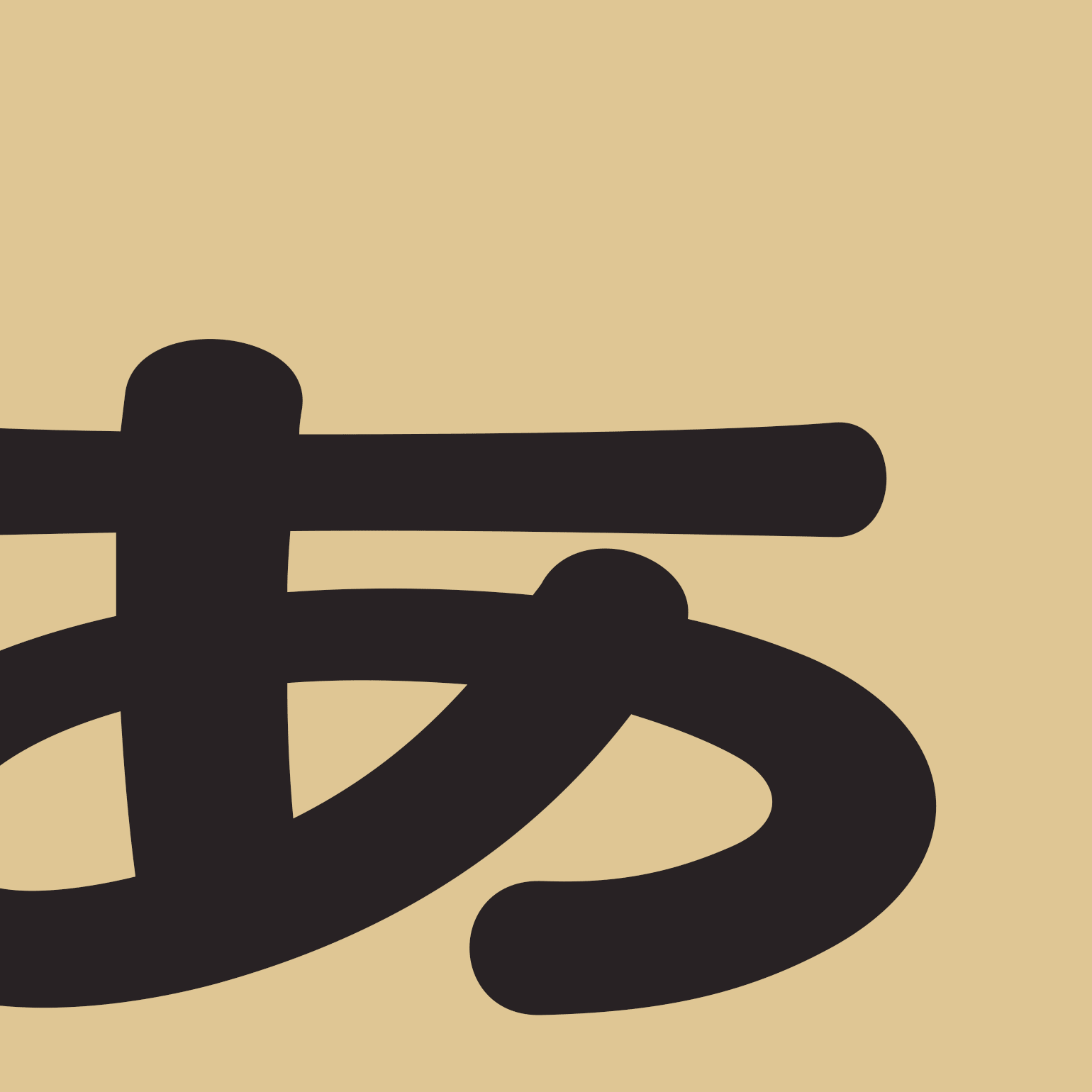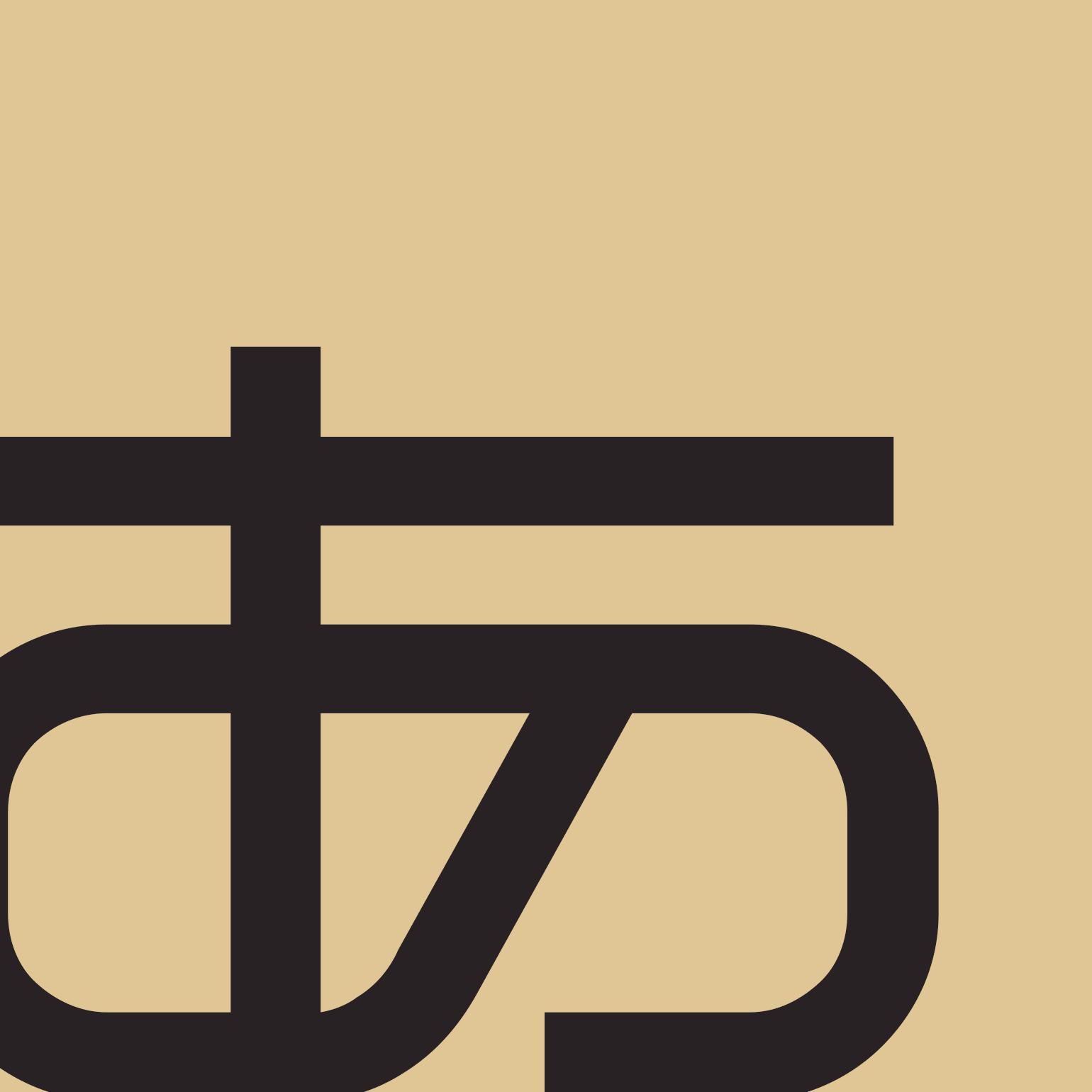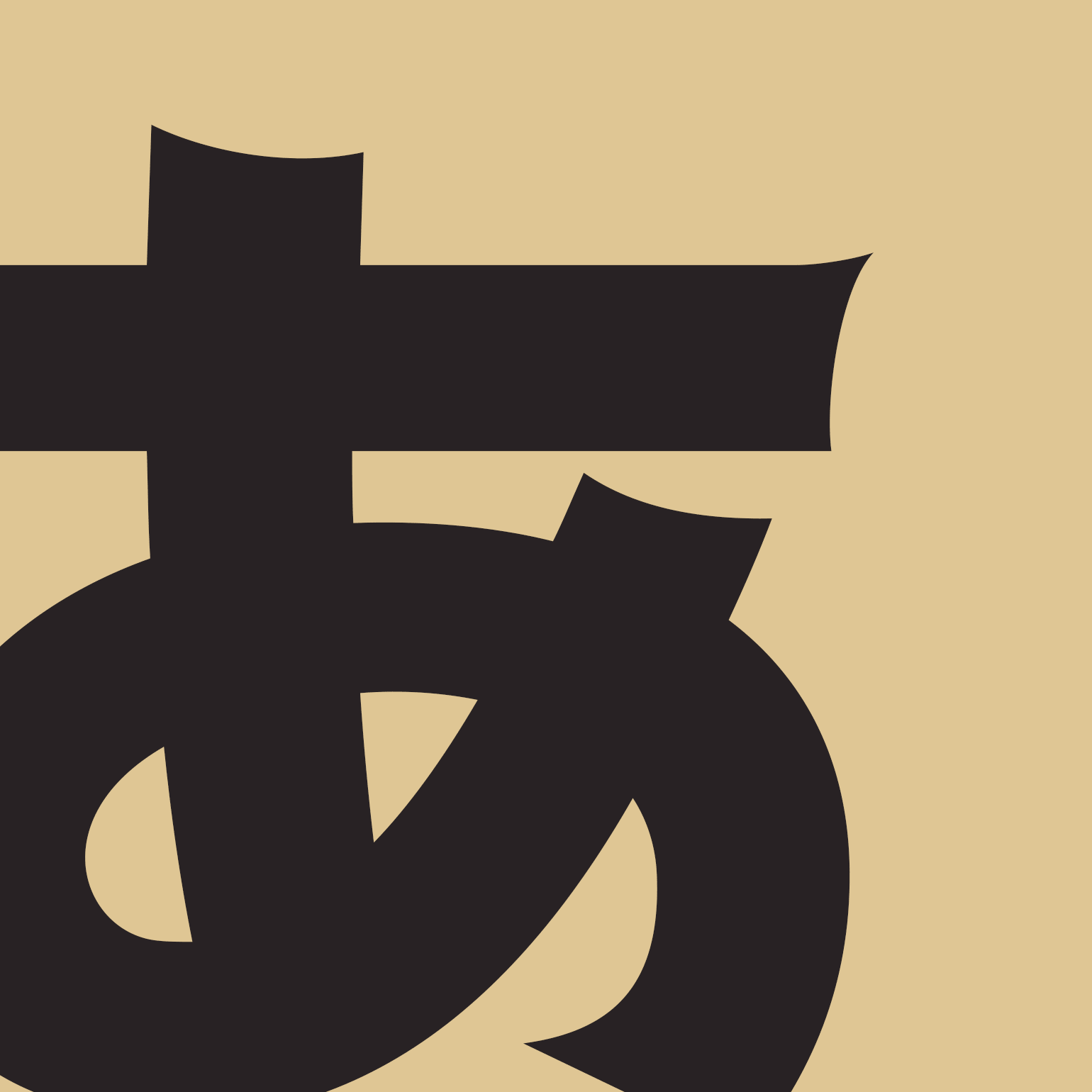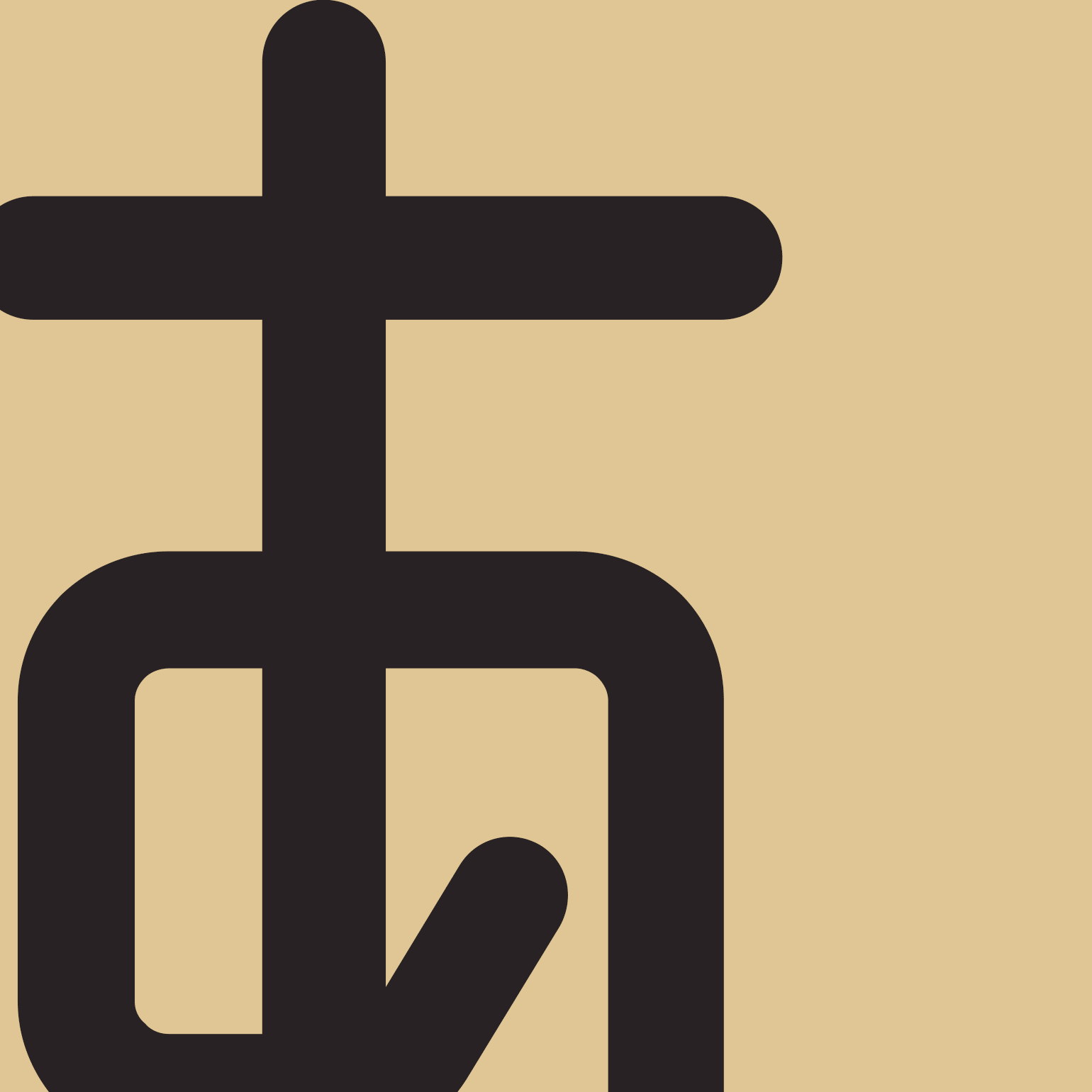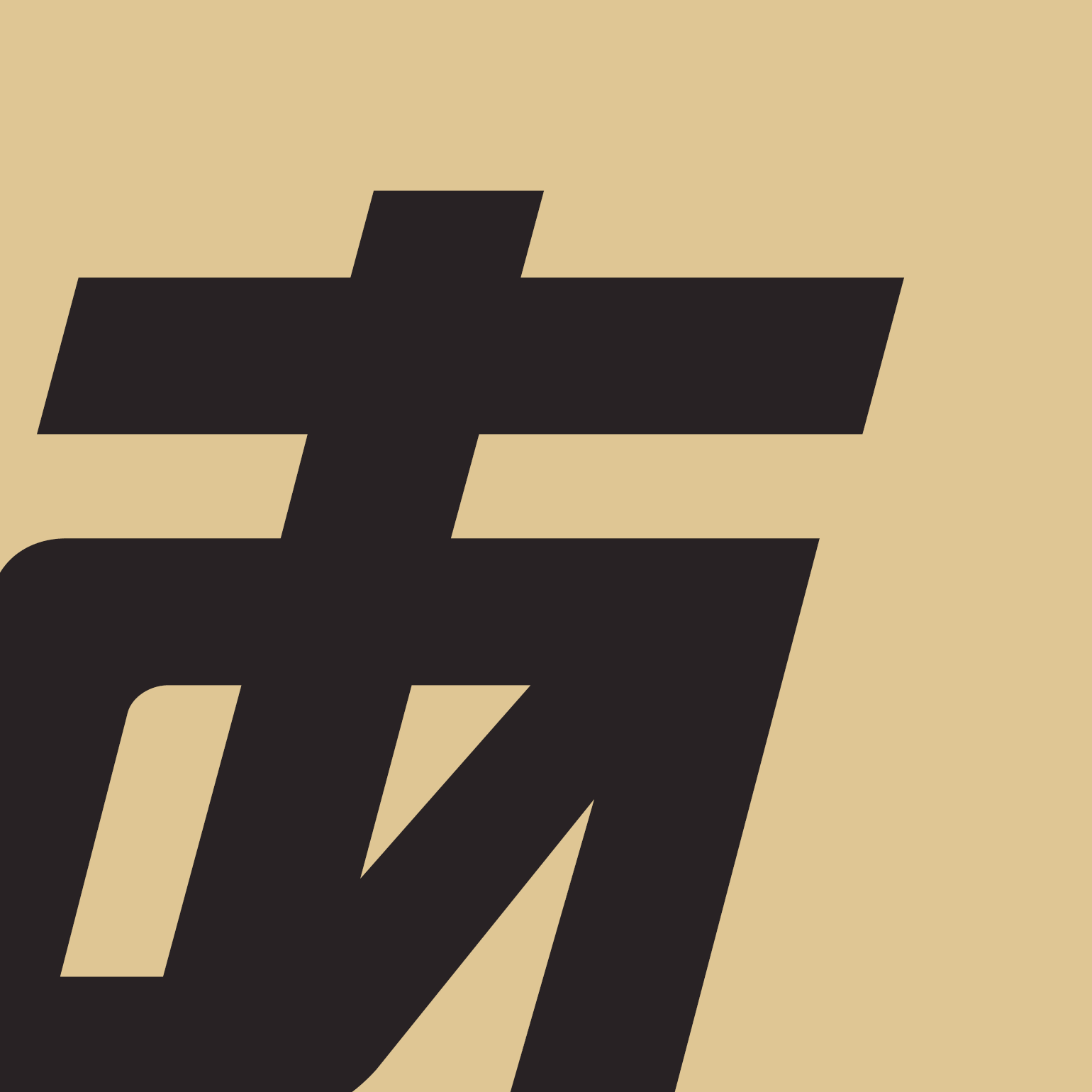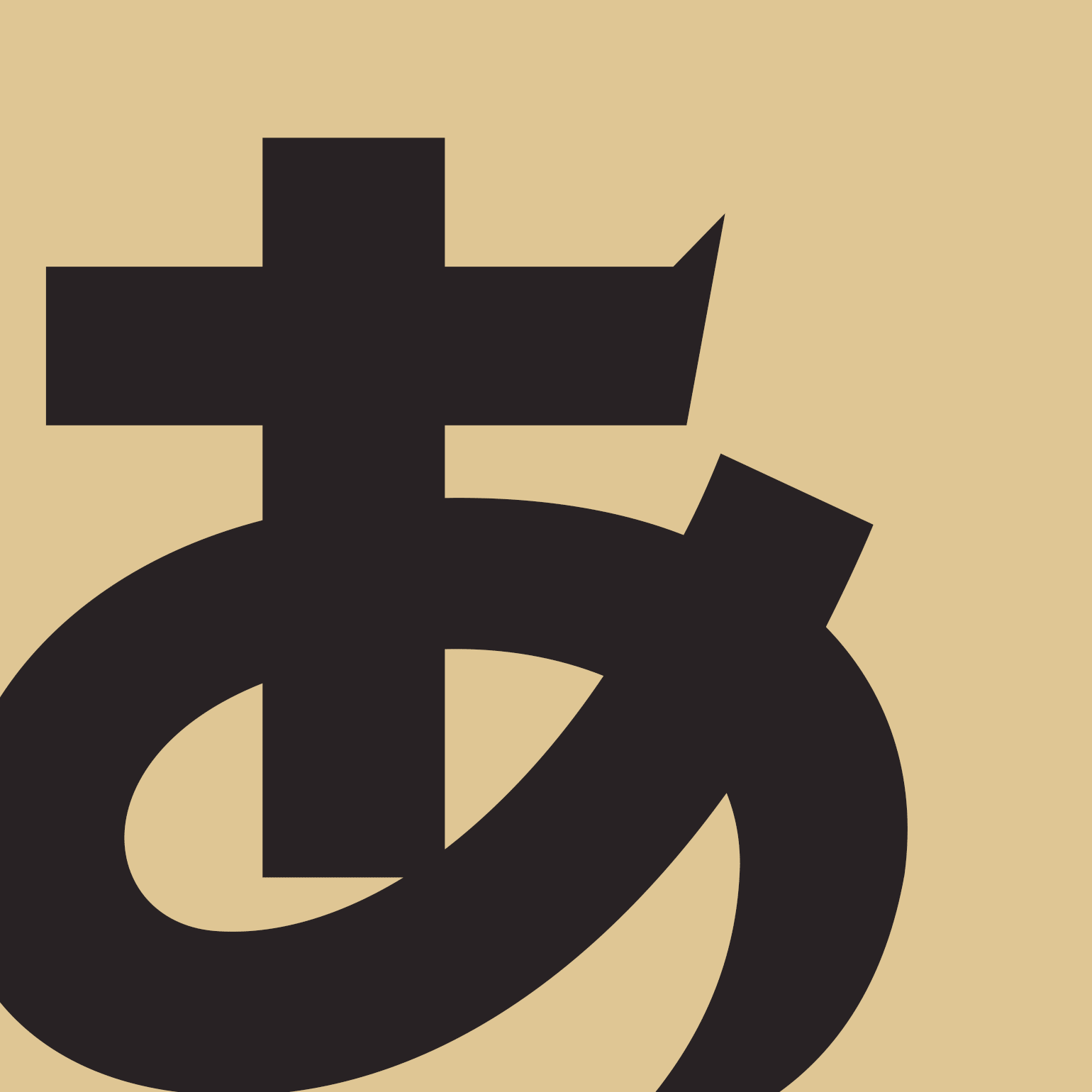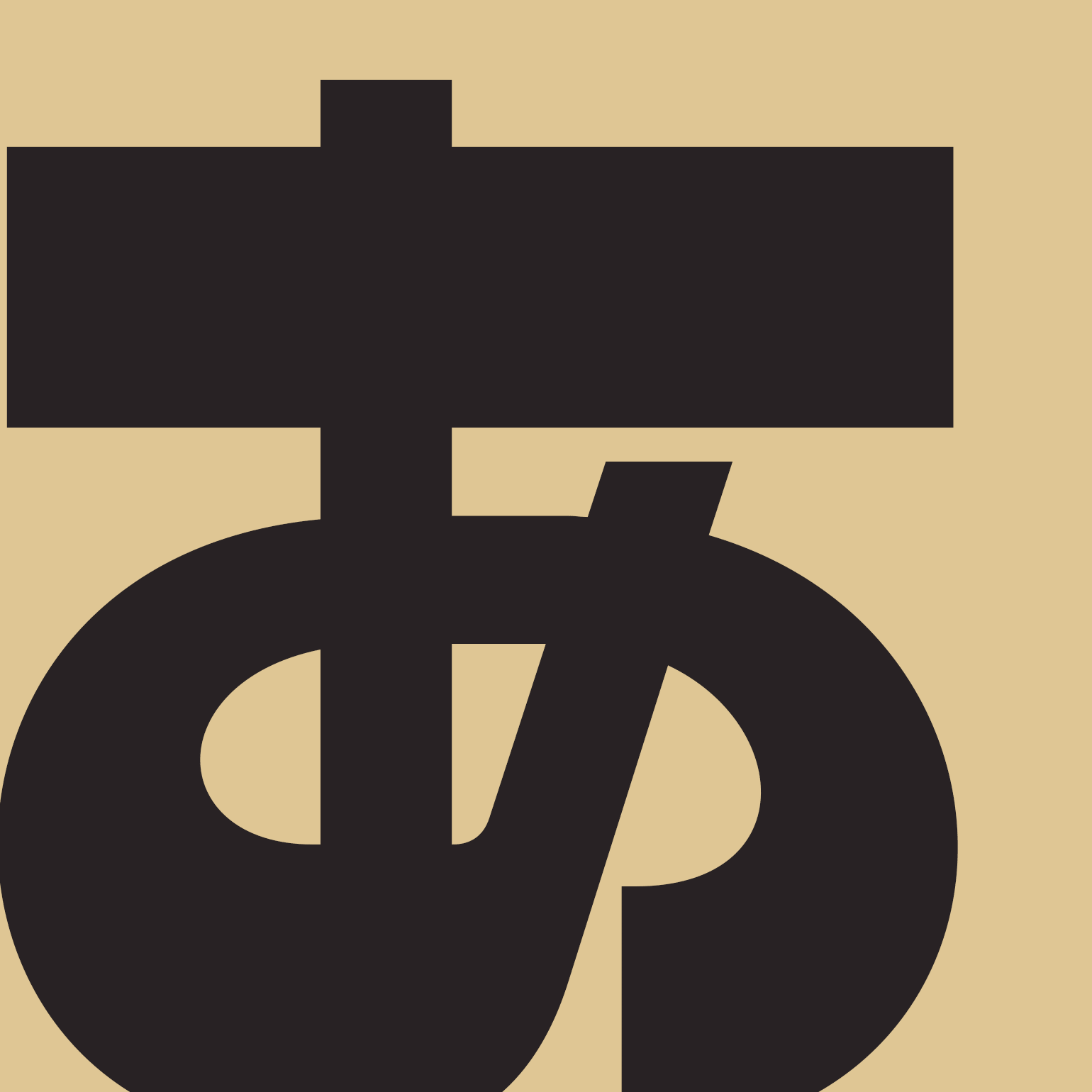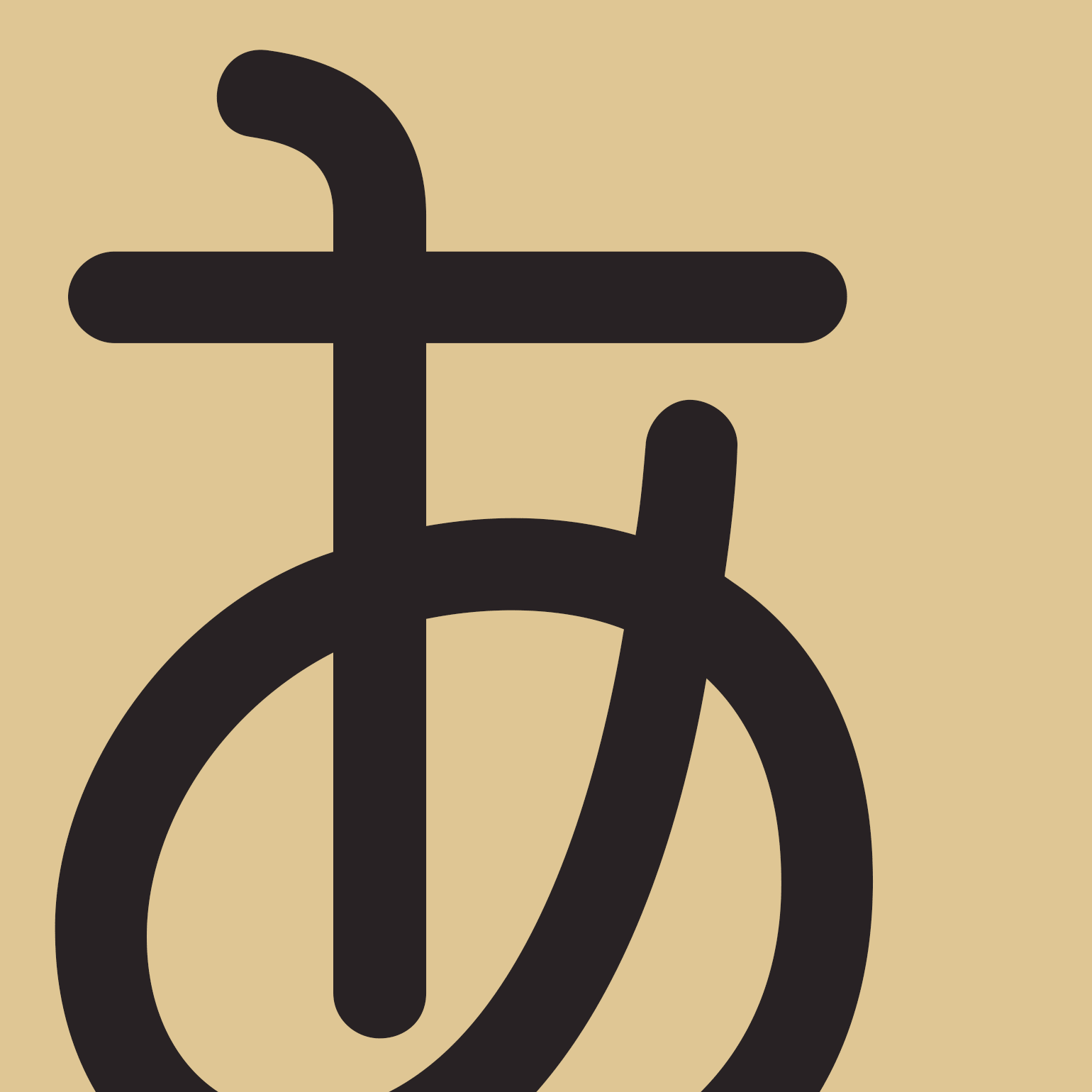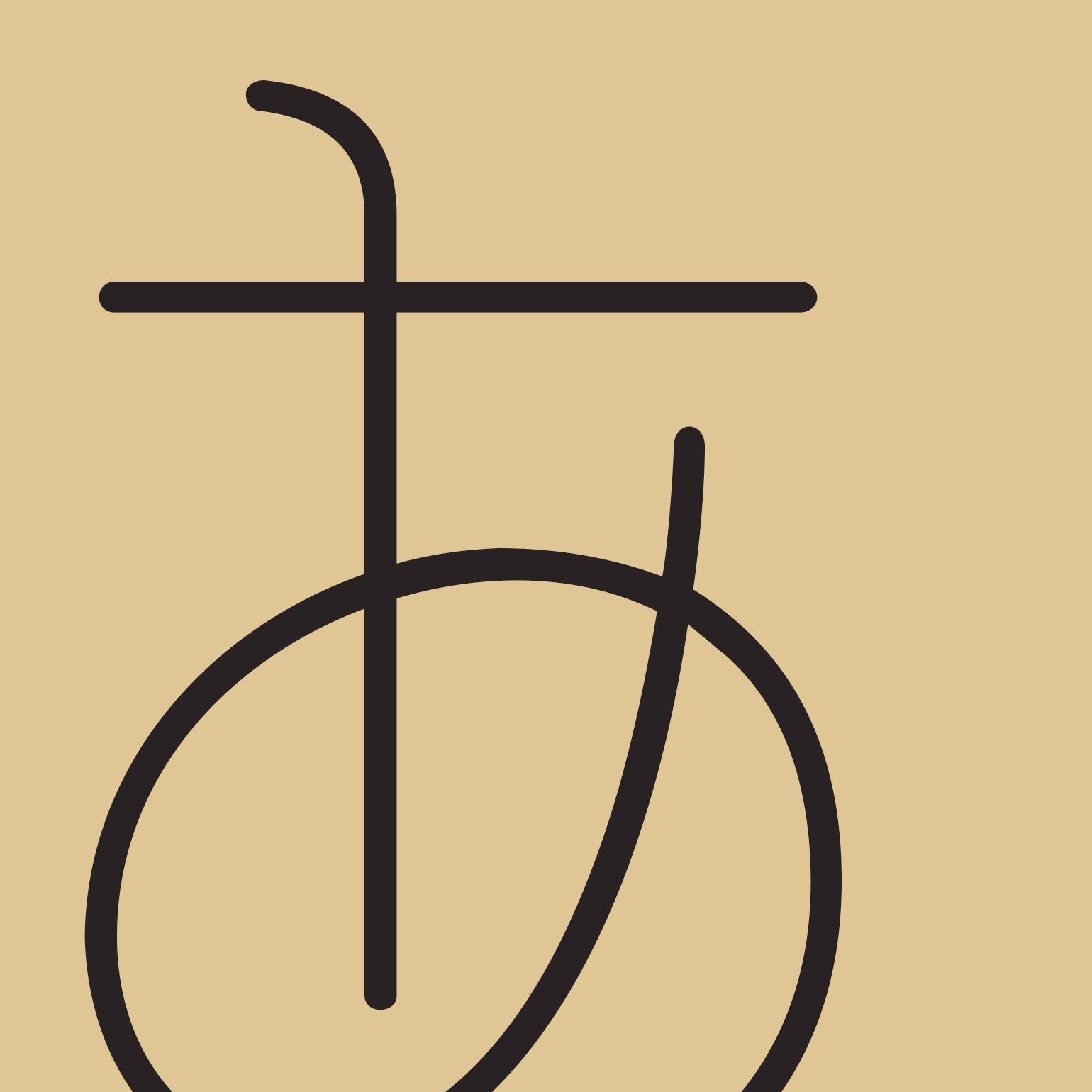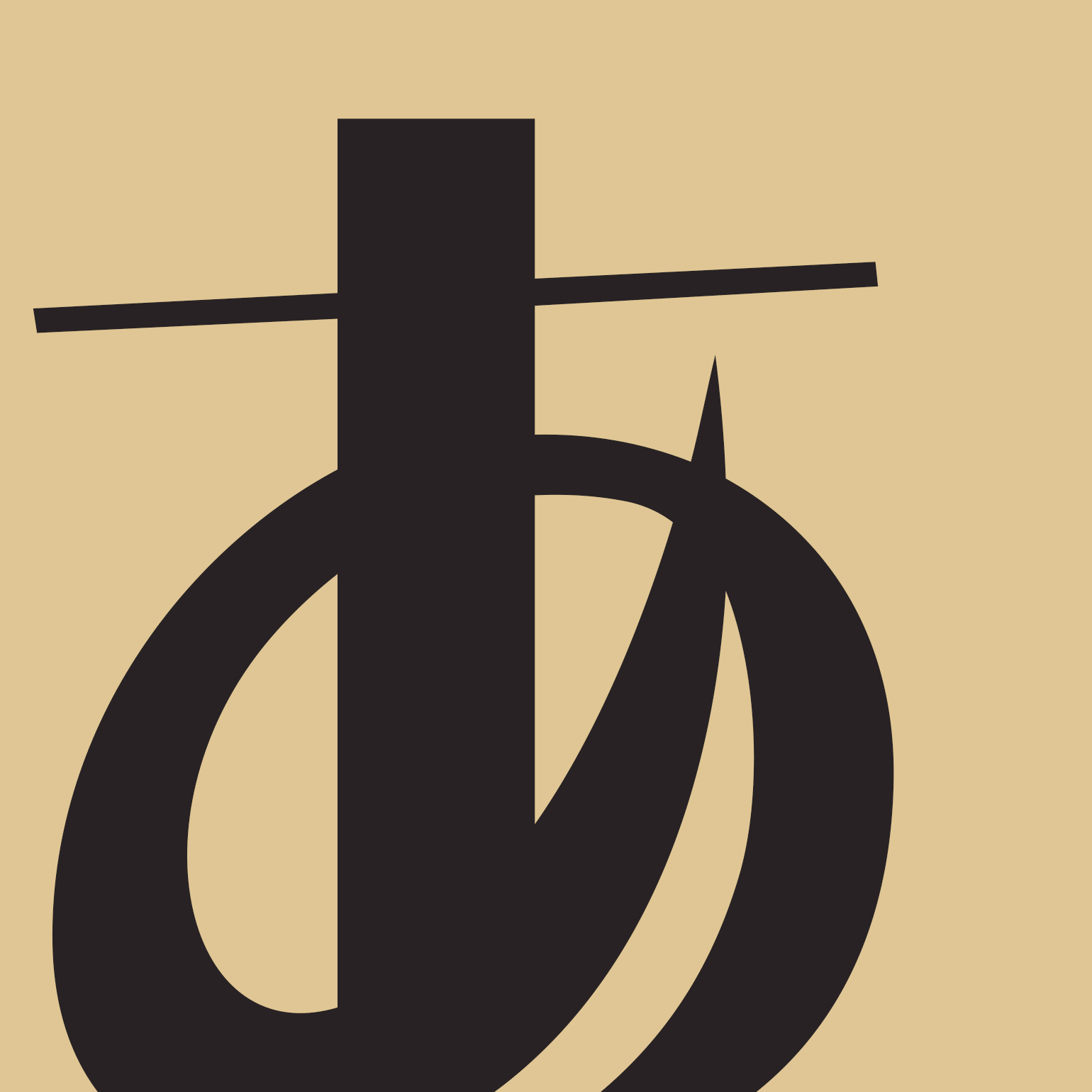
シンプルな手書き風の書体でありながら、デザイン性を損なうことなく、かわいらしさがあふれています。新鮮で自然な雰囲気が感じられ、人々に心地よさを与えます。まるで旅先で気ままに綴られた日記のような自由さとリラックス感が漂っています。
素朴な線幅と、わずかにざらついた質感を持つ手書き風の書体です。全体的に素朴で親しみやすい雰囲気があり、やや左に傾いた字形が視覚的な美しさとバランスの良い文字組みを実現します。製品パッケージやアニメーション、ゲーム、ビデオ制作など、さまざまな用途で活用できます。
この書体は、丸みを帯びた柔らかな線と変化に富んだデザインが特徴です。字形は大胆で、遊び心にあふれています。ハイライトのアクセントが文字に軽やかさを加え、全体的により生き生きとした印象を与えます。絵本や児童書、広告、アート作品、看板、チラシなど、幅広い用途で多彩な表現が可能です。
この書体は、かわいらしい手帳風のフォントです。自由で柔軟な構造に加え、丸い点の筆画が視覚的な楽しさを演出し、個性を際立たせています。全体的に無邪気で純粋な雰囲気があり、温かく癒やしのある印象を与えます。
このフォントは素朴で自然な雰囲気と自由な筆致が特徴です。細やかな筆触で描かれた丸みのある線が、温かみと手描きの味わいを感じさせます。高い視覚的表現力を持ち、手帳、児童書、動画 Vlog、個性派ブランドデザイン、広告など幅広い用途に適しています。
清新で自然な雰囲気を持つフォントです。流れるような筆致にブラシの質感を加え、自由で伸びやかな印象を与えます。意図的に引き延ばした点画が、力強さとリズム感を演出します。広告、タイトル、説明文、映画字幕など、多様なデザイン用途に適しています。
筆致の太さに変化があり、巧みさを素朴さに隠しつつ、抑揚のあるデザインが特徴です。筆画の絶妙な切れ間が、軽やかさと自由さを演出しています。全体のスタイルは剛と柔を兼ね備え、柔軟でありながらも素朴で重厚な印象を持ち、豊かな奥行きを感じさせます。
古隷書体を基にデザインされた古風のフォントです。書写特有の飛白を残し、字形と筆画の間に適度な余白を設けています。筆致は生き生きとしており、素朴さの中に巧みさが感じられます。伝統的な字形の枠を超え、現代アートを融合させた、書道美あふれるフォントです。
文字の形は平らで幅が広く取り、筆画の形づくりに円弧対称のデザイン意識を加えて独特の芸術的な雰囲気を演出します。芸術作品、ポスター、広告デザイン、ビデオ制作におすすめです。
文字の結び目は優雅で、ストロークの先端と末端の変化は安定感を求める、滑らかで力強く美しいリズム感に満ちる書体です。斜体のデザインにより文字の印象はエレガントで、美しい現代的な感じを与えます。 新聞や雑誌、書籍やポスター、メディアコミュニケーション、プロモーションなどに幅広く使用できます
ふっくらと丸みのフォルムを意識しながら、ボディは柔らかくしてかわいらしく筆画の太さのコントラストが強い書体です。フォントの特徴は無邪気で生き生きとしているところです。 絵本や児童書、アート作品、広告デザイン、ビデオ制作などに活用できます。
全体的に特徴的なデザインを施した手書きフォントは、一部の筆画が下向きに引き伸ばされ、シック且自由の感覚が自ずと生まれます。文字自体が強い視覚的な表現を持っています。雑誌、書籍、芸術作品、パーソナル・ブランディングに適しています。
カジュアルでスマートな感じの面相で描いています。筆画は一致しており、子供っぽさとかわいらしさを失うことなく、人々に無邪気さと輝きの感覚を与えながら強い視覚的魅力を持っています。絵本や児童書、製品パッケージ、広告デザインなど幅広く使用できます。
コンパクトな骨格を持ちながら、文字の結び目は安定しており、疎密を兼ね備えた筆遣いで貫いた書体です。ゆるくて不器用な感覚を出しながら、鮮やかで芸術的な面白さに満ちています。ビデオ制作、アート作品やプロモーションに適しています。
ダイナミックなウエイト表現に面白さを加え、温かみのある手書きフォントです。絵本や児童書、広告デザインやアート作品、どんなジャンル・用途でも使えます。
滑らかな運筆、一気呵成に仕上げた印象の書体です。手書きと書道スタイルが組み合わされ、市井の雰囲気を出しつつ、文学的でレトロな魅力があります。ポスター展、本の表紙、パッケージング、店舗の看板のデザインに活躍できます。
巧緻な字画、風になびく花びらのように小さく繊細な筆遣いが特徴です。全体的な感触はスマートで繊細、目を楽しませてくれます。 絵本、動画配信、パッケージデザインや広告のコピー、看板などに使えます。
筆画のデザインは自然で美しい書体です。シンプルな字面を保ちながら、曲線優美の特徴があって現代の感覚で味わい深いの設計です。広い範囲に、特にハイエンドファッションブランドのイメージデザインとPRに適用します。
丸くてゆるい雰囲気に、行書の章法とアートフォントの美感を融和した書体です。美しく洗練された自由気ままな線と字形の大小はまちまちで、全体的にリズム感を持たせています。また、古代書体の雰囲気があり、アート作品や個性的なブランドデザインのプロモーションなどに活用できます。
ゆったりした気分で描いていて、つるつるした紙へ細い平筆で素直な感じが富んでいます。メリハリがあり、字が右上に傾いてすっきりとしています。息をしている間に、自由な感覚が生まれてくるような視覚表現力があります。
細い面相で描いて、文字の形にあまりこだわらないのが特徴です。ゆっくりと気ままな気持ちで描いて適用性がかなり高いです。この書体は子供の絵本、芸術作品、広告デザインなどの視覚環境に適用して、きわめて強い応用空間があります。
太目の丸筆でゆっくりと描いています。楽しい気分で描くとかえって大胆な感じが生まれて、子供の手書き文字みたいにかわいくて自由な書体です。
字面率が抑えられた設計のため全体的にやや小ぶりですが、生き生きとした筆遣いや、トメ・ハネ・はらいが軽やかなユーモアに富んだ書体です。
細部のデザインでは復雑な特徴をつけず、基本に戻った文字本来の素朴さと美しさを楽しめるような設計を施しています。
字面に対して広く特徴的な骨格を持ちながら、文字全体のバランス感を保った頑丈な佇まいが、テクノロジー感を失わない現代的な印象を演出しています。
漢字の口(くち)の一部分が途切れていることが文字の特徴を際立たせ、そこへインパクトのあるエレメントが加わることで、テンポの良さを字形に実現しています。
軽やかで自由な線と、左右非対称の自由なズレを受け入れた枠に縛られない設計が特徴的です。デザインに軽やかな彩りを与えます。
どこかの街角で、いつかの作品で、縁が摩耗するほど時が経っても、存在感と可読性を失わない文字たち。存在感を放つウエイトと、可読性。
まぶしい朝日で輪郭が欠けた岩をイメージしました。オーソドックスなゴシック体を基調とした岩のような素朴さと裏腹に、ポップなシーンにも馴染む安定感。
蛍の舞う川辺のように、涼しい面持ち。特徴的なうろこや点、はらいが新鮮で、含む空気はどこまでも爽やかな書体です。
凛々しい佇まいの黒松から着想を得ています。ダイナミックなウエイト表現にモダンなエッジを加えて、端正な面持ちの中にもしっかりとした芯が感じられる書体です。
楽フォント
ユニークなあそび心満載のアクセントが妖しく戯れる、楽しくも幻想的な書体です。見出しとなる場所でひときわ魅力的に、印象的に。
楽フォント
面相筆で描いたような筆使いが特徴的な書体。
細長くスマートな字面は優美ですが、点部分に円形デザインを採用し、心地いいアクセントに。
楽フォント
縦画と横画の線幅のコントラストによって生み出される圧倒的存在感と、滑らかでやわらかいカーブの調和が特徴。
重量のある密度の高いデザインでも、高い可読性を保っているのがポイントです。
楽フォント
古代書体の優美な上品さを纏った、シャープな線が現代的でモダンな印象の書体。
個々の文字の中にユーモアのあるアクセントを施し、抑揚ある文字組を演出します。
楽フォント
書房体に施した趣向を保ちながら、ウェイトを重くしました。
繊細なデザインワークを、より鮮明に。
楽フォント
筆を勢いよく抜いたようなエッジの効いたハライと、力強く墨溜まりを作ったトメの表現がバランスの良い緩急を生みだしています。
楽フォント
直線的設計によるコンパクトな堅牢さと、優しいアーク化エレメント。
短めの横線は斜めにデザインし、スマートな中にもより印象的な刺激を。
楽フォント
文字のトメ・ハネが跳ね上がるようなデザインは文字組みをポップで明るく、楽しげに。
リズミカルで、活力のある書体ですが、統一感を持ち安定した設計です。